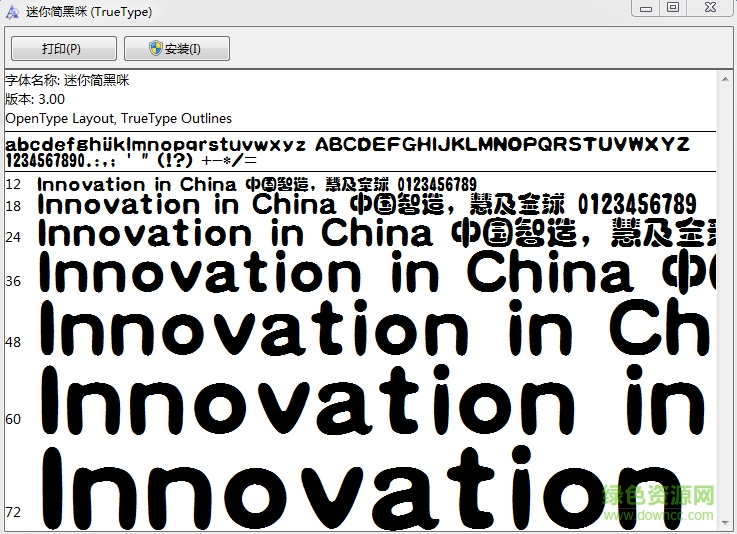
jheimi是什么字體?jheimi字體是一款圓滾滾的迷你簡(jiǎn)黑咪字體,筆形柔和,字型十分飽滿,稚氣又生動(dòng),可以用作卡通設(shè)計(jì)或廣告設(shè)計(jì),此款字體也是女性用戶比較常用的,非常的具有特色,有需要者趕緊來(lái)綠色資源網(wǎng)下載收藏吧!